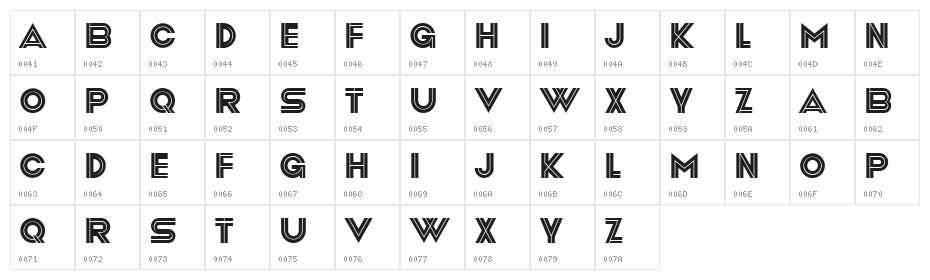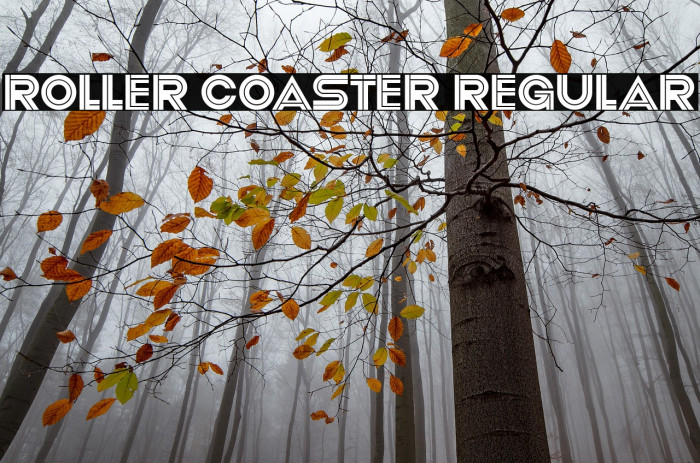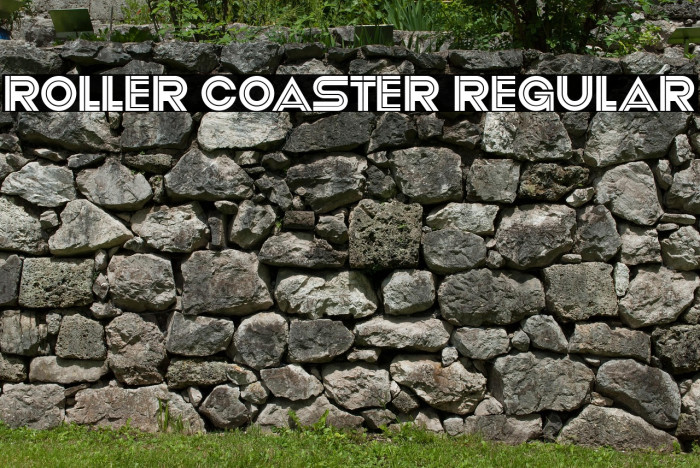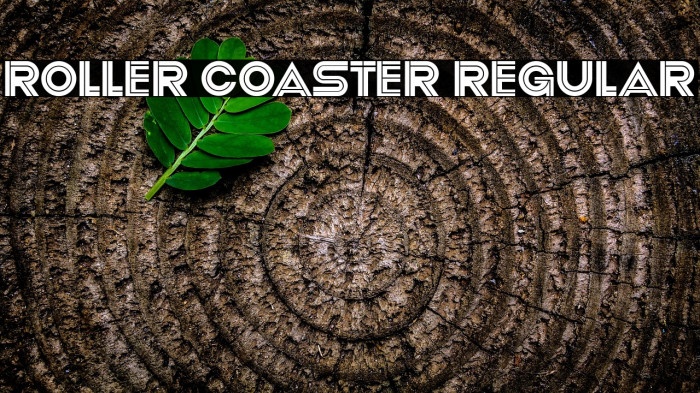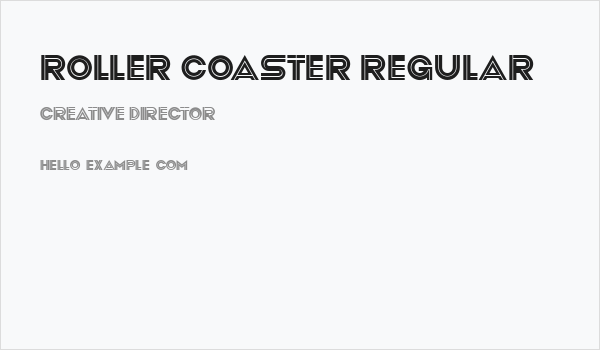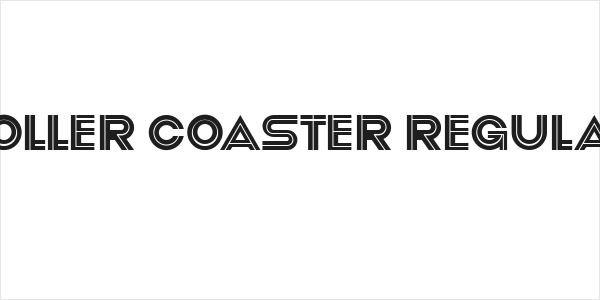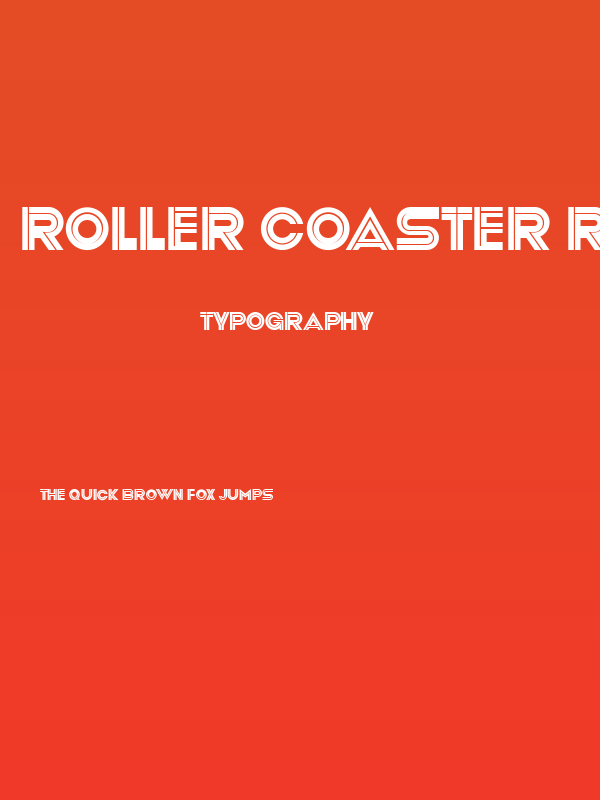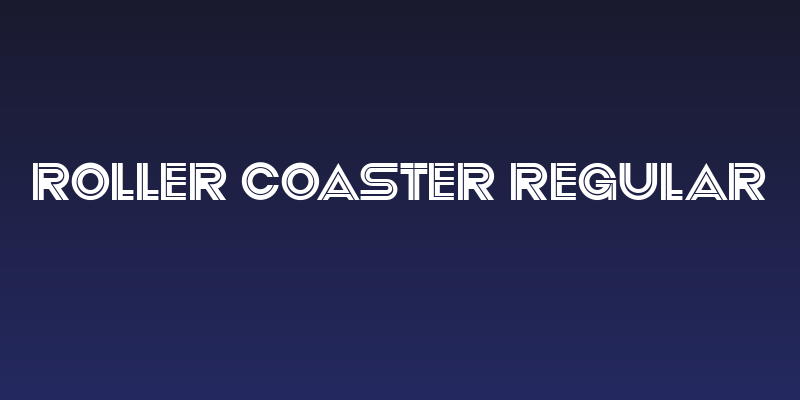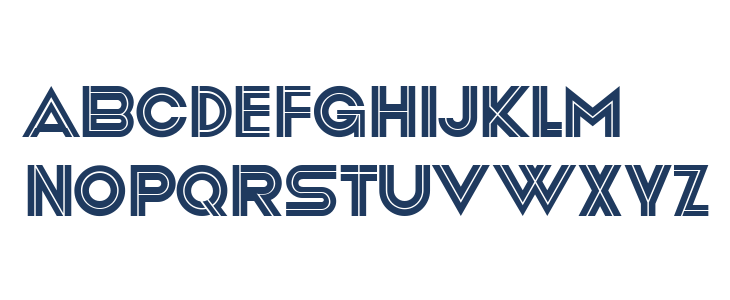
Roller Coaster Regular Font
✎ Art Deco
| Progetti proposti | Ideal for branding, poster design, and any project requiring a bold, modern aesthetic. |